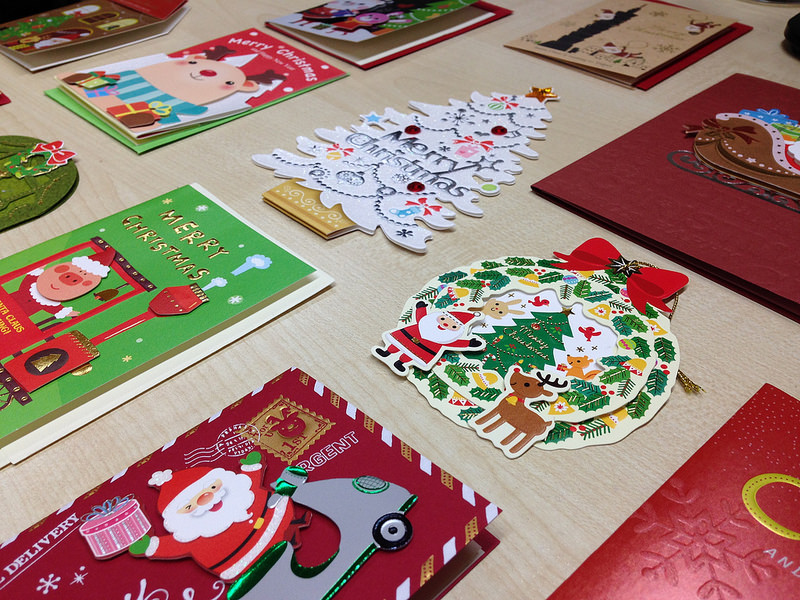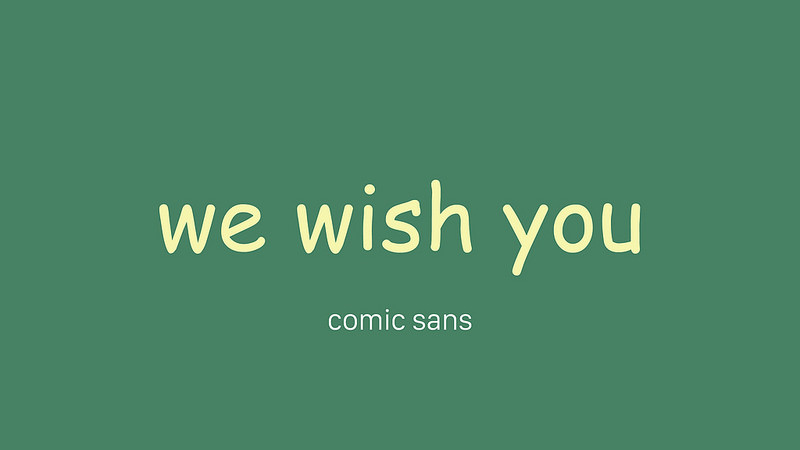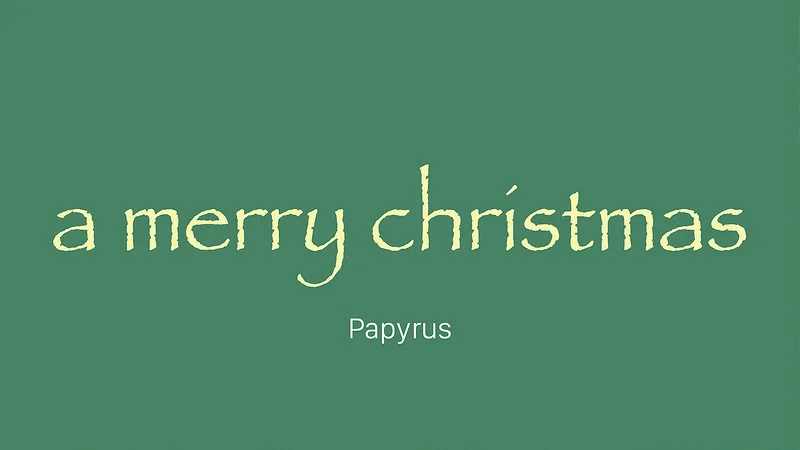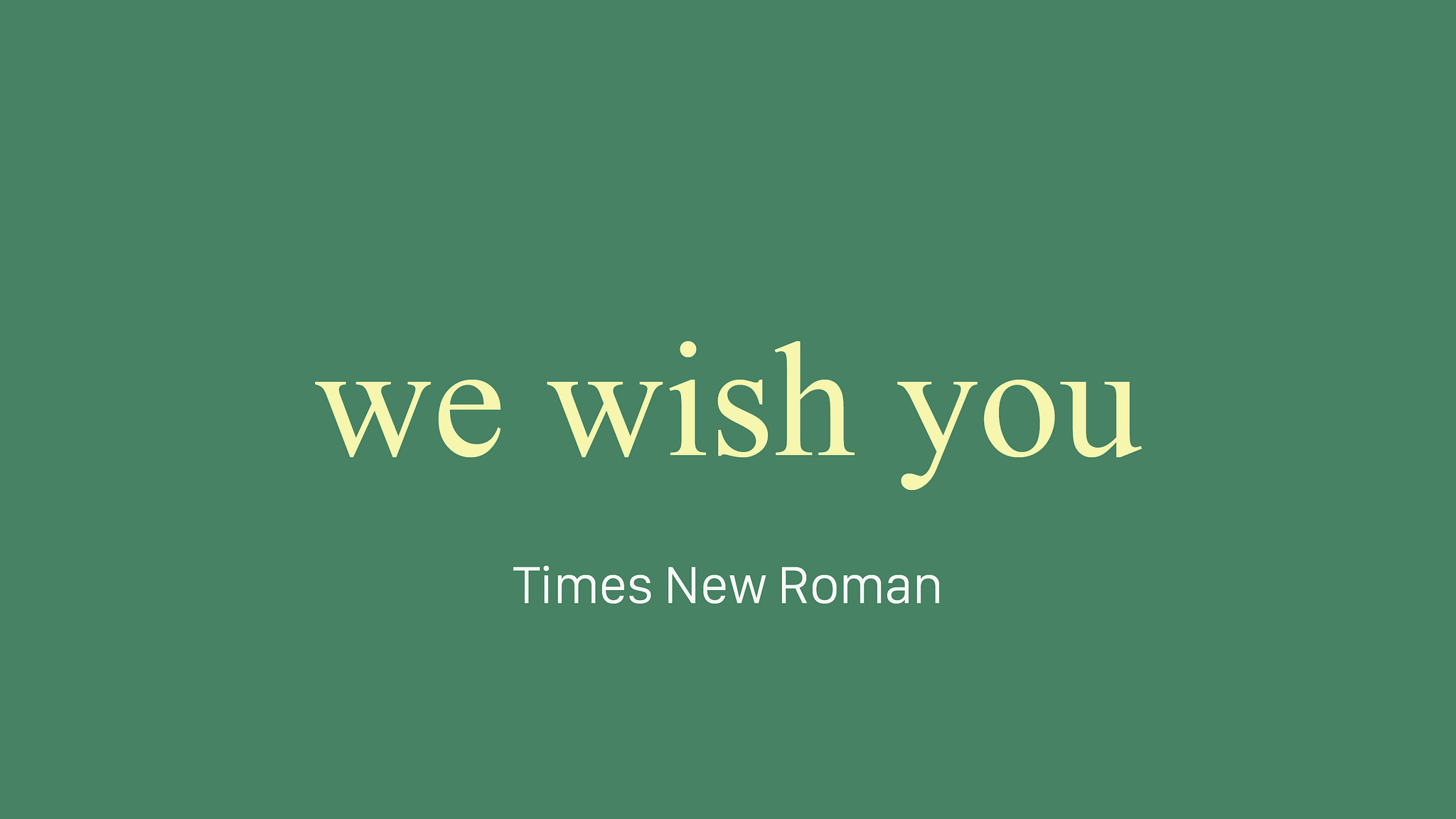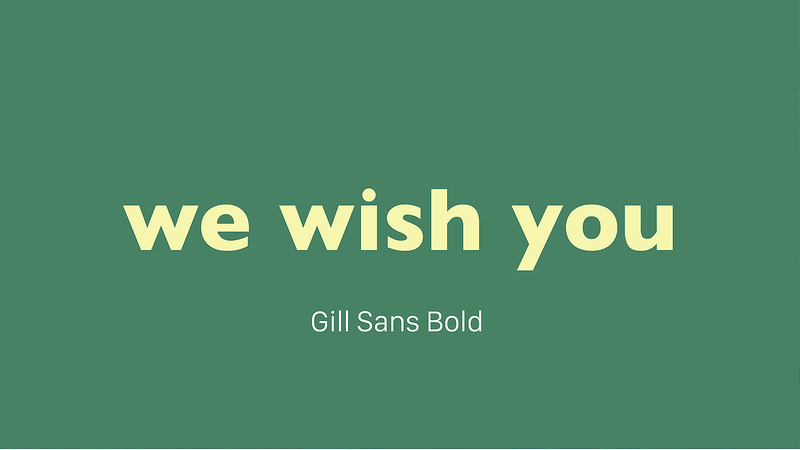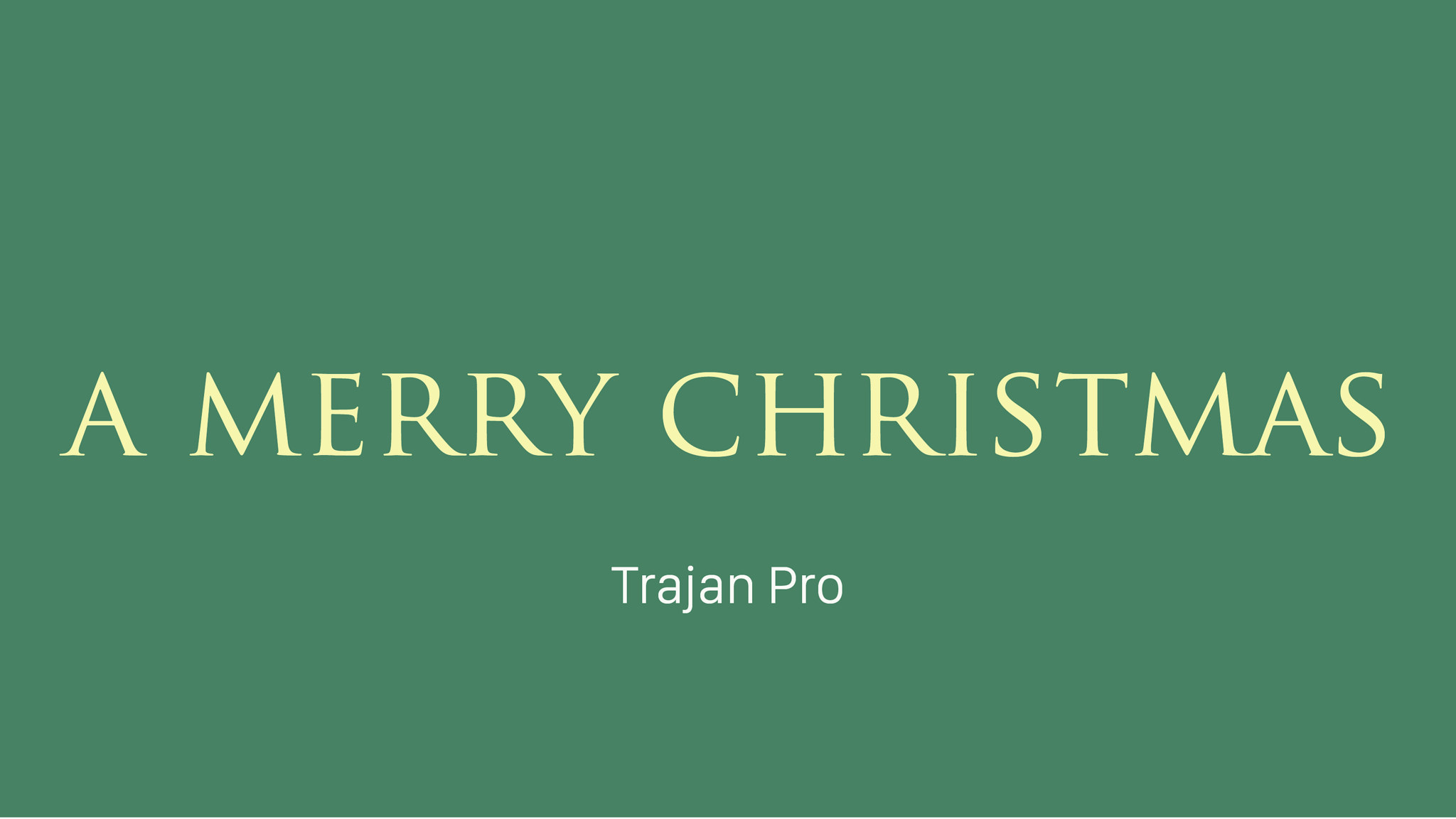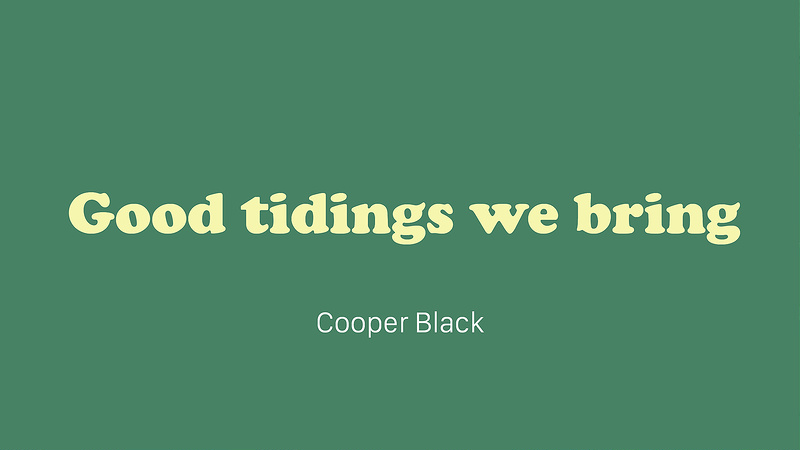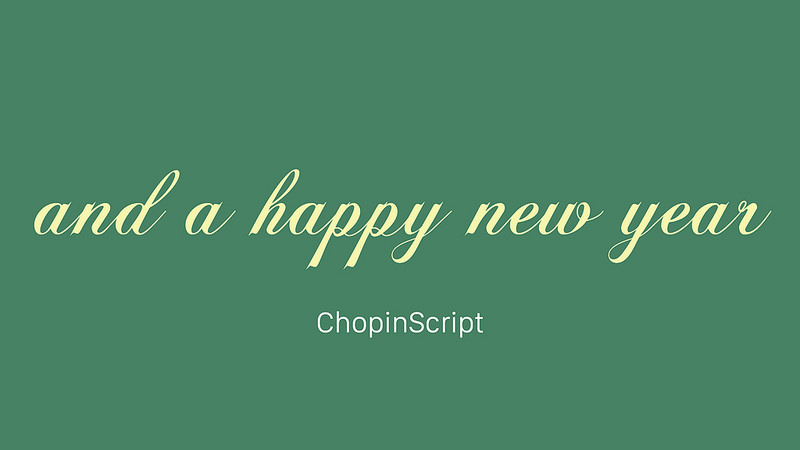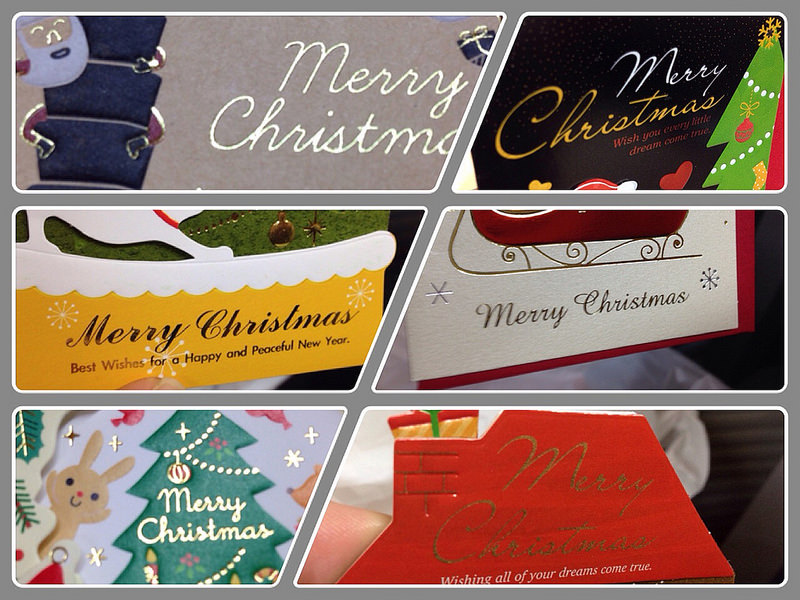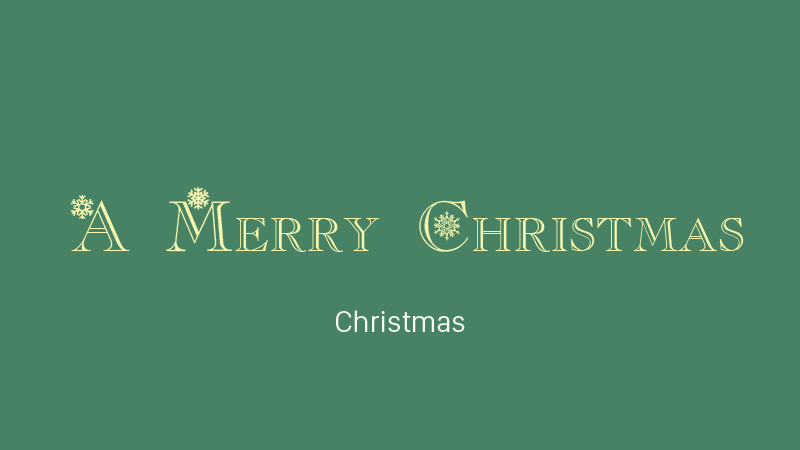
聖誕節就在下週了。從字體來觀察,這真是個一成不變的節日,從小到大的聖誕卡片字體都差不多。根據我們實地的市場調查(其實就是從公司附近的文具行買了十多張卡片回來研究)這些字體差不多就是以下這些:
1. 聽說用了就會很快樂的 comic sans。這個字體在西方受到抵制的程度跟在台灣的某體簡直不相上下。救護車上面用了這種字體好像連送醫急救都變成很快樂無害的事(真的有這種事,詳參 Just My Type),所以引起眾人的惱怒。
2. 某字體在西方的親戚,主打莎草紙書寫質感的 papyrus。本來是想要重建一種在莎草捲軸上書寫的復古感,但到最後不但不復古,反倒看起來還有點噁心?至少歐美許多設計師這麼認為……
3. 設計師忘記換字體了的 Times New Roman。身為一套幾乎可說全世界的電腦裡都有的字體,而且用在報告、報紙上表現甚為優秀的字體,居然出現在卡片上,讓無誠意度簡直飆高直至 99%。
4. 看起來很可愛但其實是 Arial 的 Arial Rounded。
5. 不知道要怎麼吐槽的 Gill Sans Bold。
6. 在好萊塢他們都說不知道要用什麼字體就用吧的 Trajan,常見於史詩、古代戰爭等題材,所以用在卡片上顯得有一點殺氣。它來源是古羅馬石柱上的雕刻字體。其實羅馬時代拉丁字母只有大寫,所以這套字型也就只有大寫。
7. 1920 年代曾經很紅,嬰兒用品很愛用的 cooper black,可能是因為肥肥圓圓的關係。
以上都是 Mac 系統裡都有的預設字型。Mac 因為預設字體豐富,可以說是設計師的好朋友。再來是老梗中的老梗,script 書法體字型。凡是聖誕節,就一定要有這種 script,要不然沒有一種櫥窗精品的感覺。
真的不騙你,他們超喜歡用 Script 的啦。難道這跟楷書強迫症是一樣的道理嗎?
不過,除了精品路線以外,我們還可以注意一個很常見的風格,就是各式各樣的有的沒的裝飾。這基本上已經跳脫展示字型的範疇,到了一個設計圖庫的誇張概念了,不信的話:
例如這個拐杖糖體
還有上面堆了一層雪的
還有這一個類似冰雪奇緣的概念
這也是一個冰雪奇緣的概念,不過可能是中世紀勇敢傳說版(可以出合集啊,反正都是迪士尼)
還有,這個,雪花、天使、融冰、蠟燭與聖誕帽熔於一爐的,呃,東西。
然後還有米奇體。
老梗的卡片們。